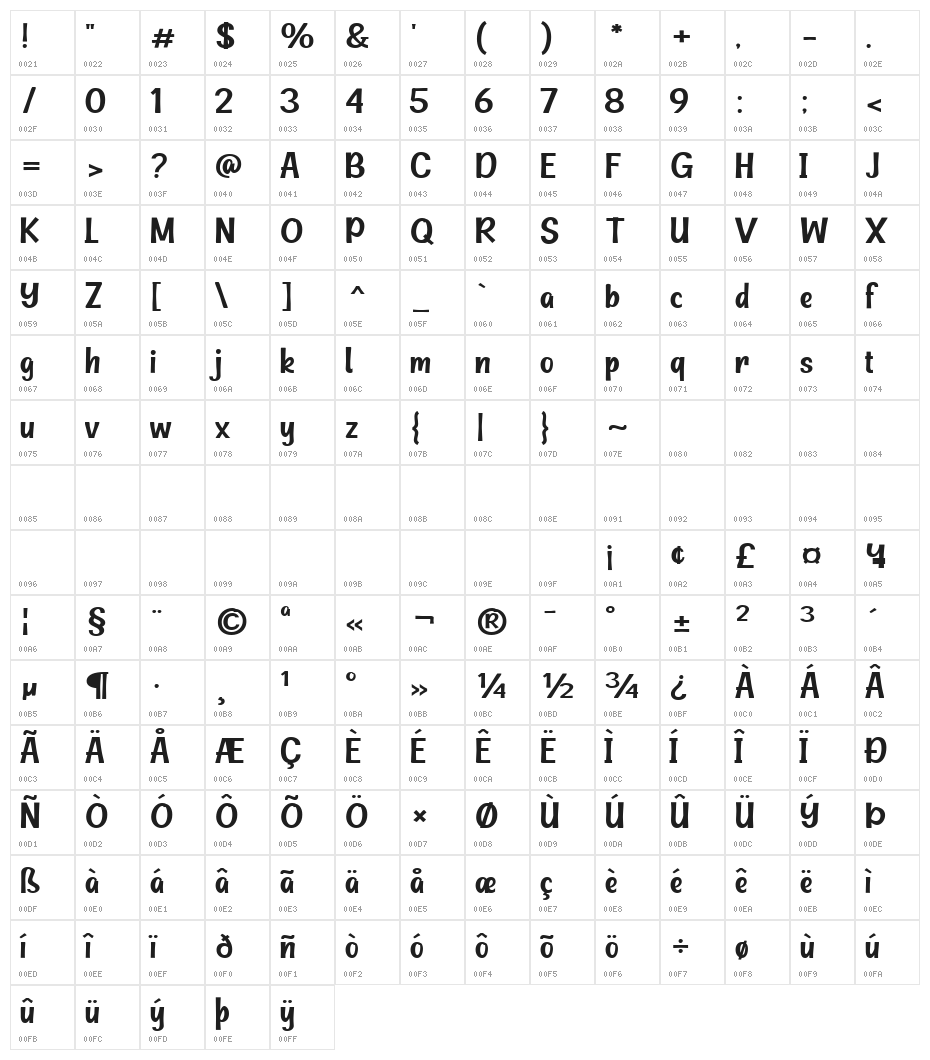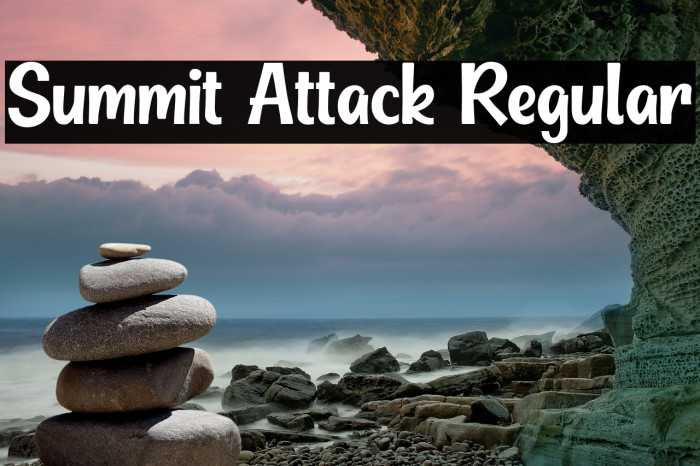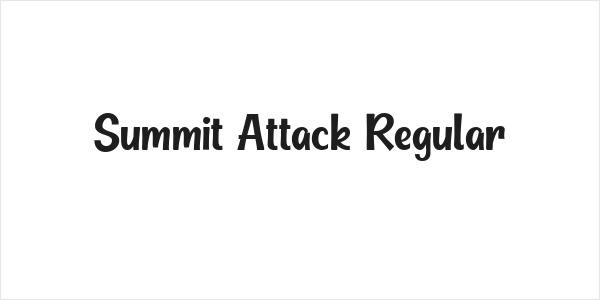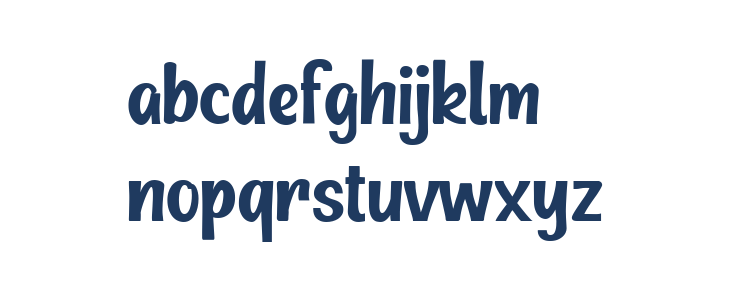
Summit Attack Regular Font
Fonts by Ali Hamidi
| Estilo general | Playful, Energetic, Hand-drawn |
| Proyectos propuestos | Ideal for children's books, playful branding, posters, and creative projects that require a lively and informal tone. |